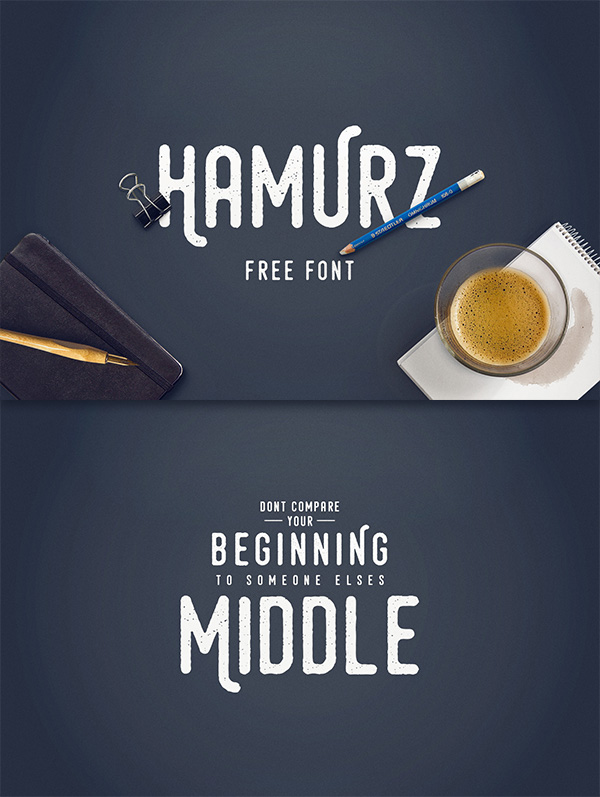
Дополнения Шрифты Татьяна Гапонова 12 марта 2016 Шрифт - Hamurz Интересный декоративный шрифт для дизайна надписей. Формат - TTF, OTF. Размер - 3 мб. Скачать Шрифт - Hamurz